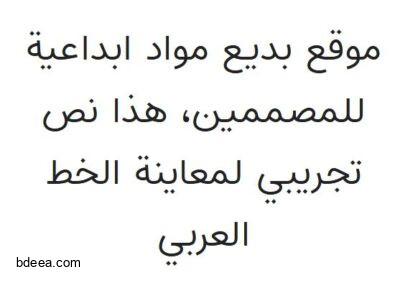
خط استداد عربي لايت Estedad Light Arabic Font
خط استداد عربي لايت Estedad Light Arabic Font يضيف نصوص وكلمات عربية بلمسة فنية مميزة الى التصاميم العربية والمطبوعات والعروض التقديمية بالكلمات العربية والارقام بشكل مميز يمكنك تثبيته على جهازك والبدء باستخدامه في برامج التصميم
يتميز بالخط بالمرونة والخفة والشكل الانيق في الكتابة والحروف يمكن معاينته وتجربة استخدامه ليضيف لك تميز الى تصاميمك